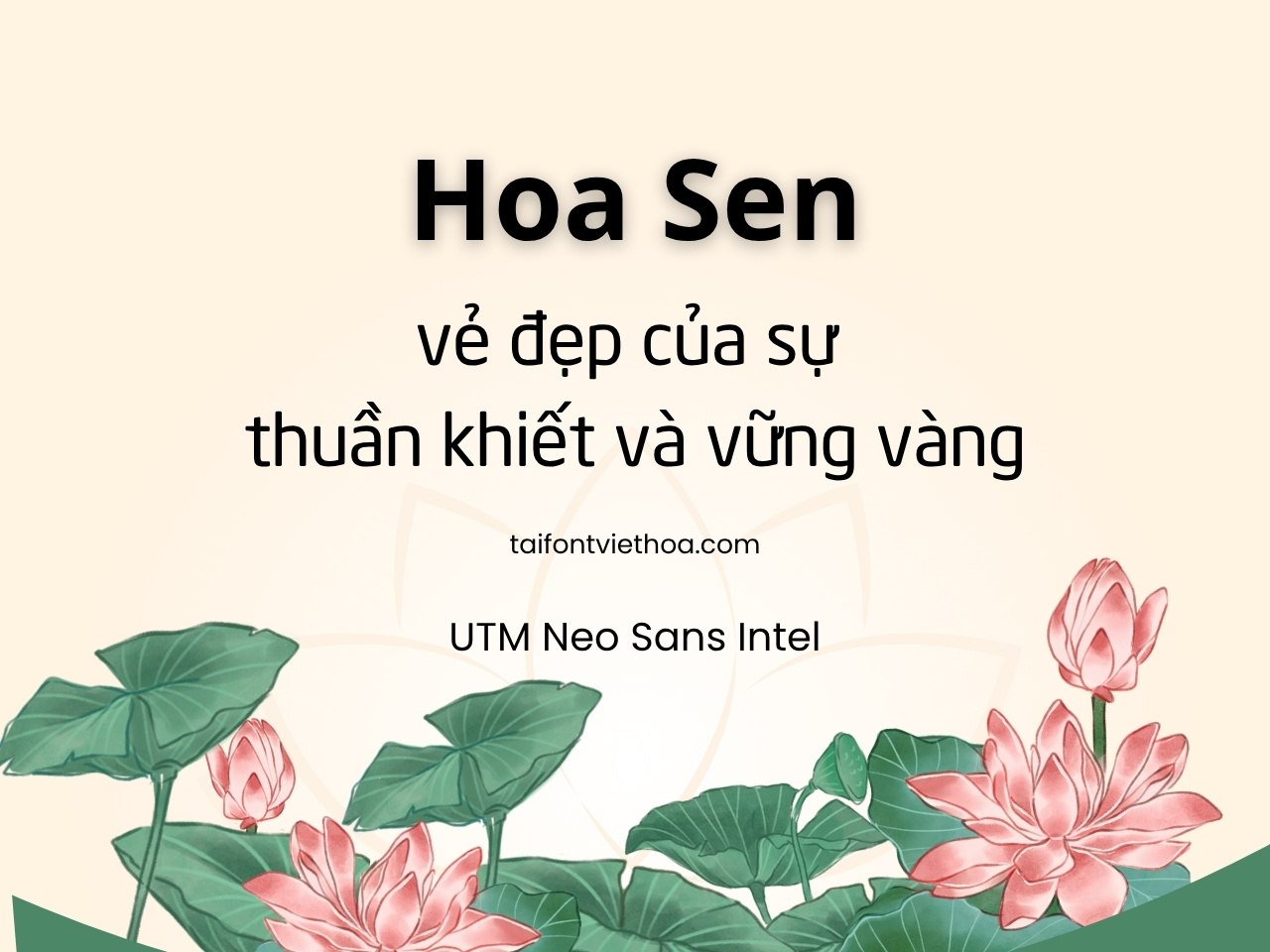
Font việt hóa UTM Neo Sans Intel đầy đủ
Giới thiệu về font UTM Neo Sans Intel Trọn Bộ
UTM Neo Sans Intel Trọn Bộ là phiên bản Việt hóa của font Neo Sans Intel – một bộ font sans-serif hiện đại, được thiết kế bởi nhà thiết kế Sebastian Lester. Bộ font này nổi bật với các nét chữ mềm mại, cân đối và tối giản, phù hợp với nhiều ứng dụng từ nhận diện thương hiệu đến thiết kế giao diện người dùng. Phiên bản Việt hóa đã được hoàn thiện để hỗ trợ đầy đủ tiếng Việt cùng hơn 200 ngôn ngữ khác, đáp ứng nhu cầu đa dạng trong các dự án thiết kế và truyền thông.
Font UTM Neo Sans Intel Trọn Bộ được taifontviethoa.com sưu tầm và lựa chọn kỹ lưỡng nhằm phục vụ cộng đồng thiết kế Việt Nam. Phiên bản Việt hóa giữ nguyên sự tinh tế và hiện đại của bản gốc, đồng thời tối ưu khả năng hiển thị tiếng Việt, rất phù hợp cho các dự án branding, quảng cáo và truyền thông đa phương tiện.
Đặc điểm thiết kế và ứng dụng của UTM Neo Sans Intel Trọn Bộ
UTM Neo Sans Intel Trọn Bộ sở hữu cấu trúc sans-serif không chân, với các nét chữ mềm mại, đồng đều và rõ ràng. Bộ font gồm nhiều biến thể trọng lượng, giúp các nhà thiết kế linh hoạt sử dụng trong nhiều bối cảnh từ tiêu đề nổi bật đến nội dung chi tiết. Thiết kế font mang lại cảm giác hiện đại, chuyên nghiệp và dễ đọc trên nhiều nền tảng.
Font thích hợp sử dụng trong thiết kế website, nhận diện thương hiệu, quảng cáo, bao bì sản phẩm, brochure, poster và các dự án truyền thông đa phương tiện. Các ngành nghề phù hợp gồm: công nghệ, giáo dục, quảng cáo, startup và thương mại điện tử.